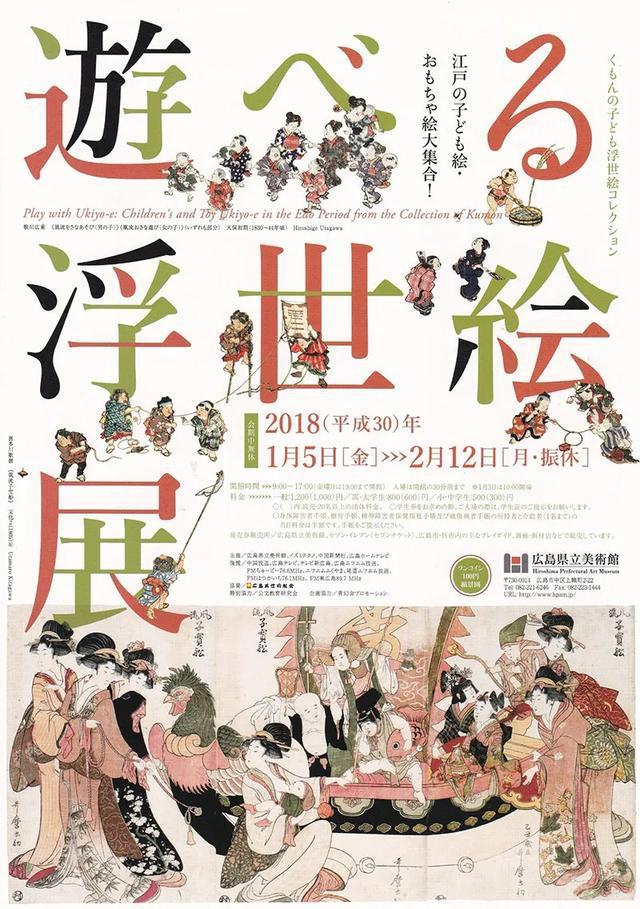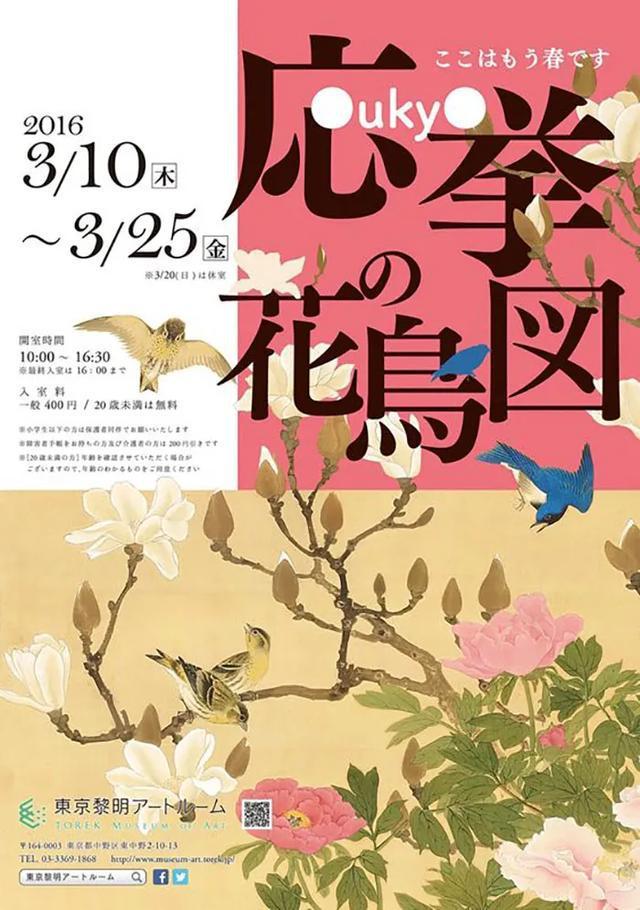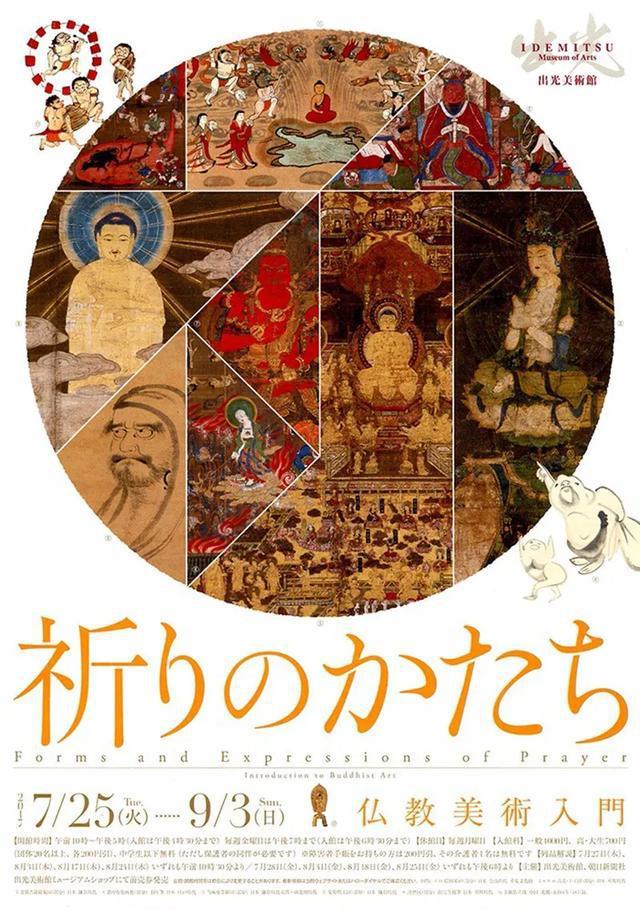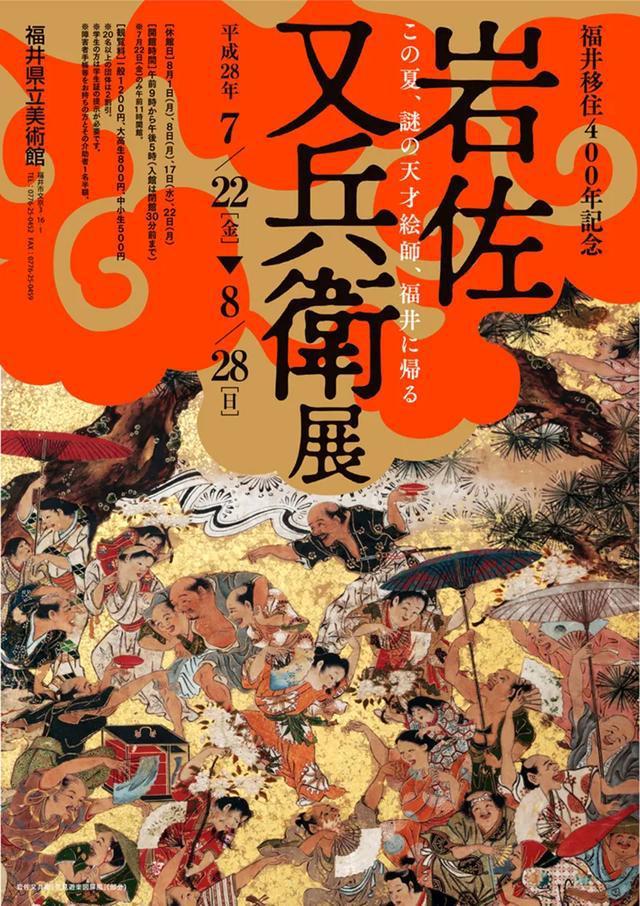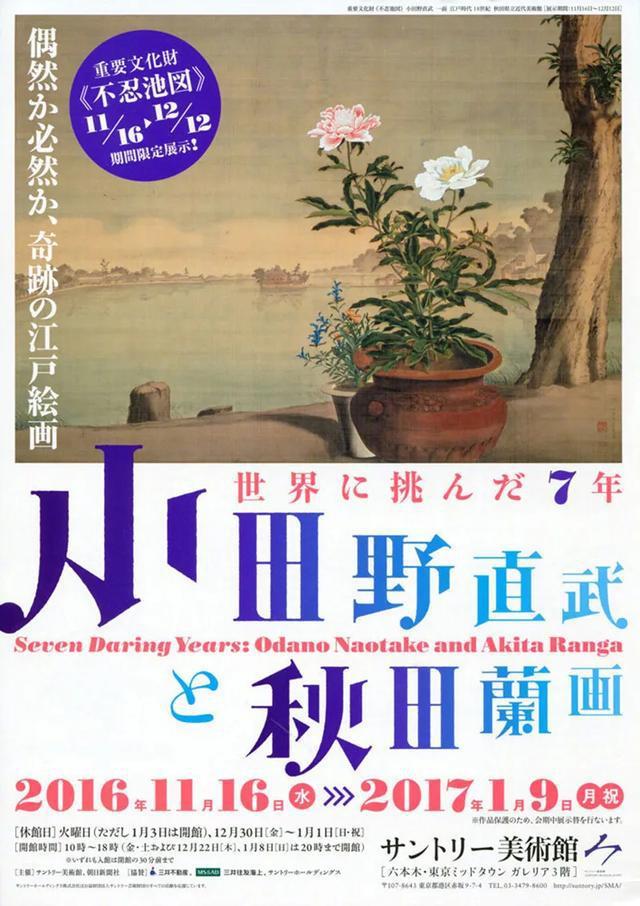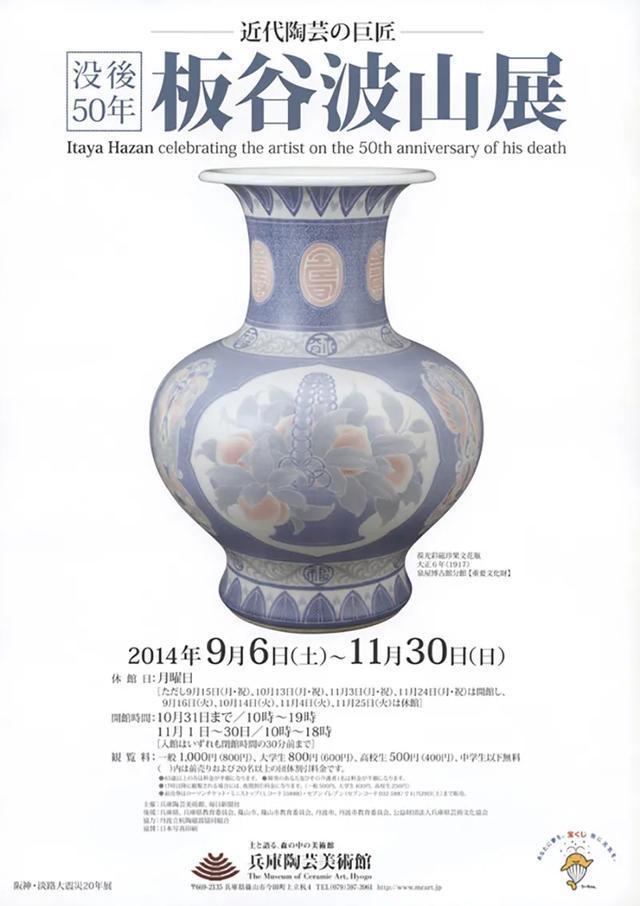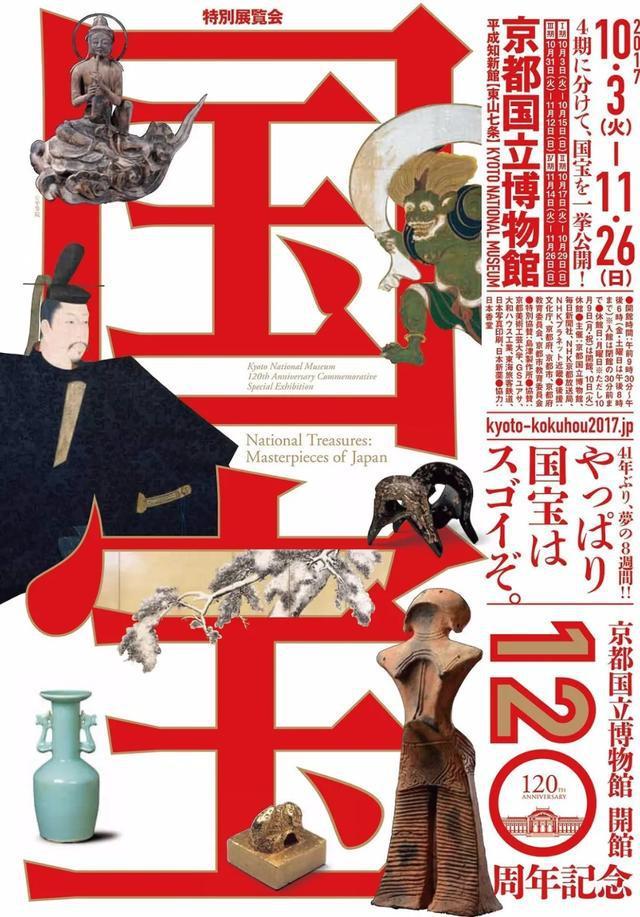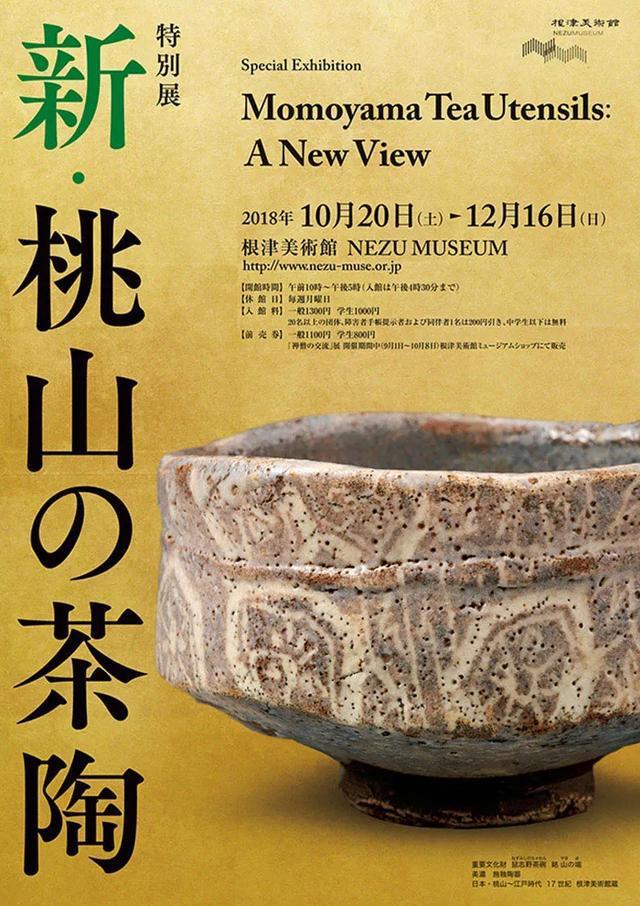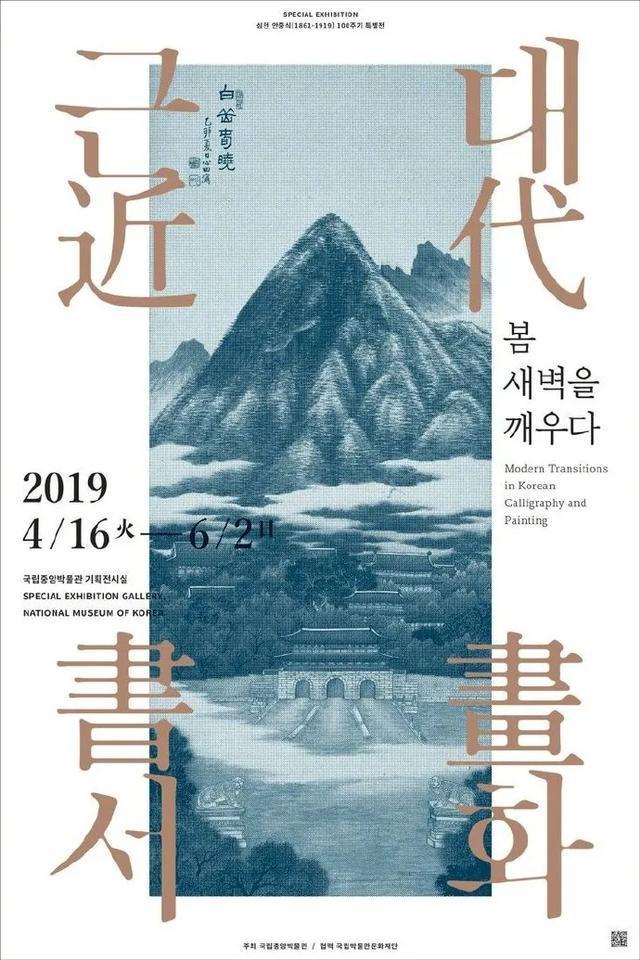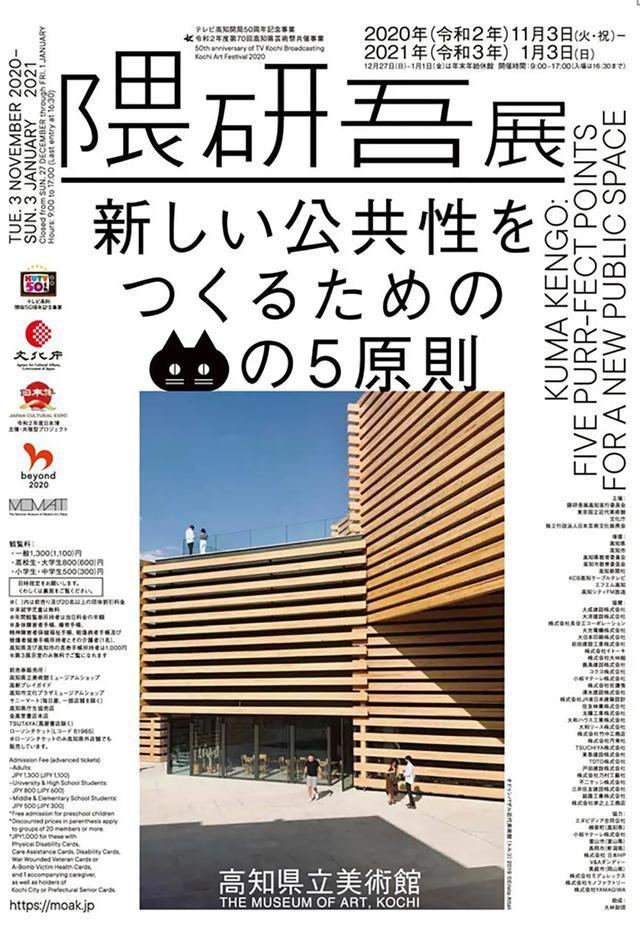
不少设计师觉得海报设计很难,特别是对于刚入行的设计师,不知道该如何下手。不知道版面如何布局,标题字体该如何编排才能突出主题。
今天这些海报设计有个共同点,就是搭配大大的字体标题。虽然画面中内容众多,但其主题突出,处理方式巧妙,整体非常和谐。
○ 上下构图
上下构图形式是将版面分割为.上下两部分,或让画面中的元素整体呈现出上下的分布趋势,主空间承载视觉点,次空间承载阅读信息,呈现的视觉效果平衡而稳定。
最典型的上下构图由”上图下字”或者”上字下图”两部分构成,图片及文字各占据一部分,不干预,能清晰明了地传达出版面的信息。
○ 上中下三段式构图
上中下三段式构图是把版面分成上、中、下三部分,把文字信息放在上下部分,图片放中间,或者是把图片放在上下部分,文字放在中间,形成上中下结构。
○ 左右构图
“左右构图”是将版面分割为左右两部分,或通过设计元素的布局让画面整体呈现出左右的分布趋势,具有平衡、稳定、互相呼应的特点。
○ 环绕型构图
环绕型构图是把元素围绕主体进行排布,并以突出画面中的主体为目的。从视觉上看,画面很稳定是把元素围绕主画面放置。但是不一定要四周都铺满元素才叫环绕型构图,至少有两边是放置元素的。
海报设计有很多处理方式,如果你不知道标题字体该如何处理,可以将标题字体放大再放大,通过强烈的大小对比来加强画面的张力,希望能给大家带来灵感。